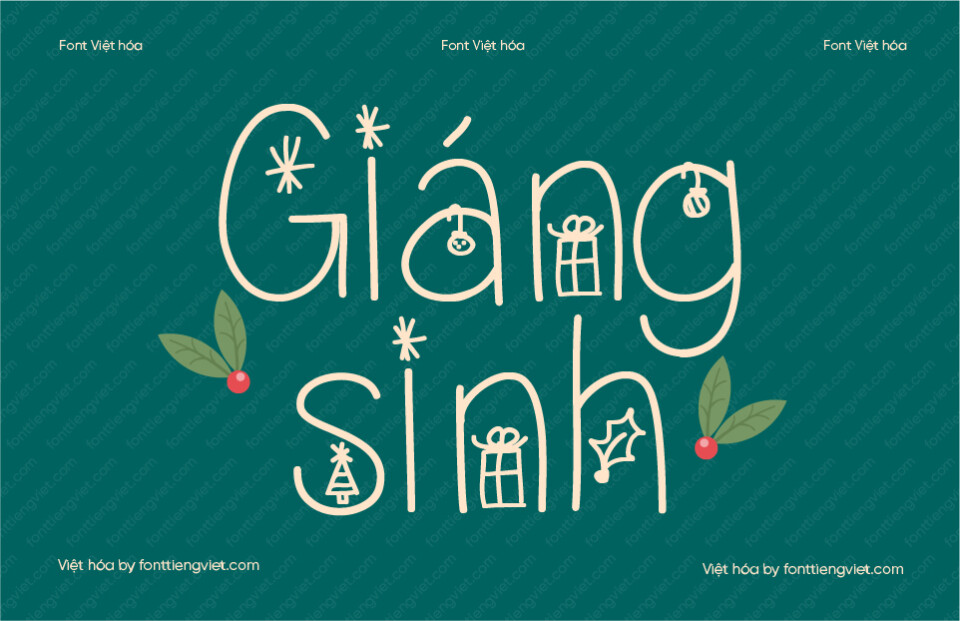
Chào đón mùa lễ hội cuối năm, việc lựa chọn một bộ Font Chữ phù hợp là yếu tố then chốt giúp các thiết kế trở nên lung linh và ấm áp hơn. Font Việt hóa 1FTV VIP ChristmasEve chính là lựa chọn hoàn hảo dành cho các bạn học sinh và thầy cô giáo khi muốn tạo ra những tấm thiệp chúc mừng hay bài thuyết trình sinh động. Bộ font này không chỉ mang nét vẽ tay mềm mại mà còn được tối ưu hóa hoàn toàn cho bảng mã tiếng Việt, giúp người dùng sử dụng dễ dàng mà không lo lỗi hiển thị dấu.
Đặc điểm nổi bật của Font Việt hóa 1FTV VIP ChristmasEve
Phong cách thiết kế lễ hội
Bộ font này sở hữu đường nét thanh thoát, mô phỏng kiểu chữ viết tay đầy tính nghệ thuật. Font Việt hóa 1FTV VIP ChristmasEve mang đến cảm giác gần gũi, gợi nhắc đến những lá thư gửi ông già Noel hay những lời chúc an lành đêm Giáng sinh. Sự kết hợp giữa các nét cong uyển chuyển và độ dày vừa phải giúp chữ dễ đọc nhưng vẫn giữ được nét tinh tế riêng biệt.
Khả năng ứng dụng đa dạng
Trong môi trường học đường, các bạn có thể dùng font chữ này để thiết kế báo tường, trang trí lớp học hoặc làm nổi bật các tiêu đề bài học trên Canva. Đối với các dự án thiết kế chuyên nghiệp, font còn hỗ trợ tốt cho việc làm banner quảng cáo hoặc in ấn lên các sản phẩm quà tặng mùa đông.